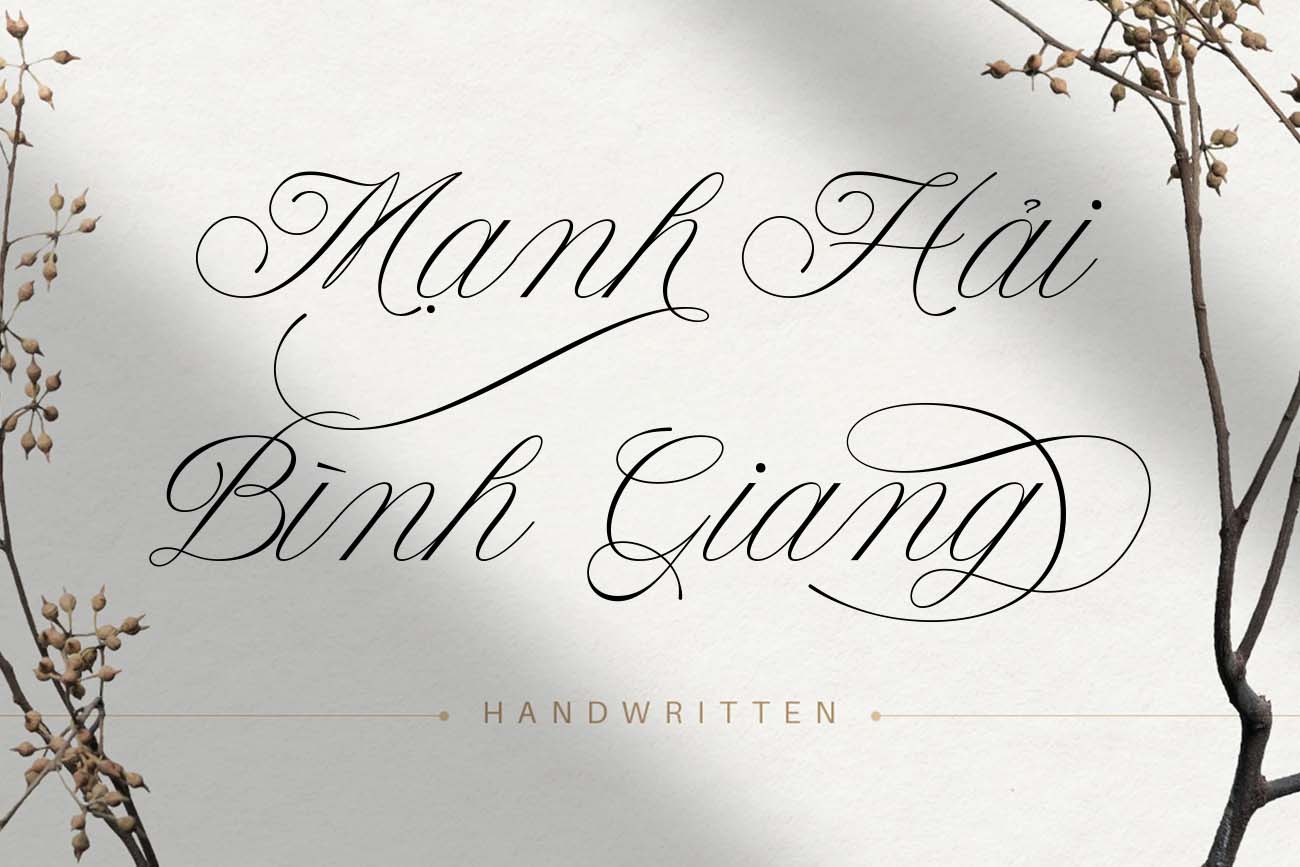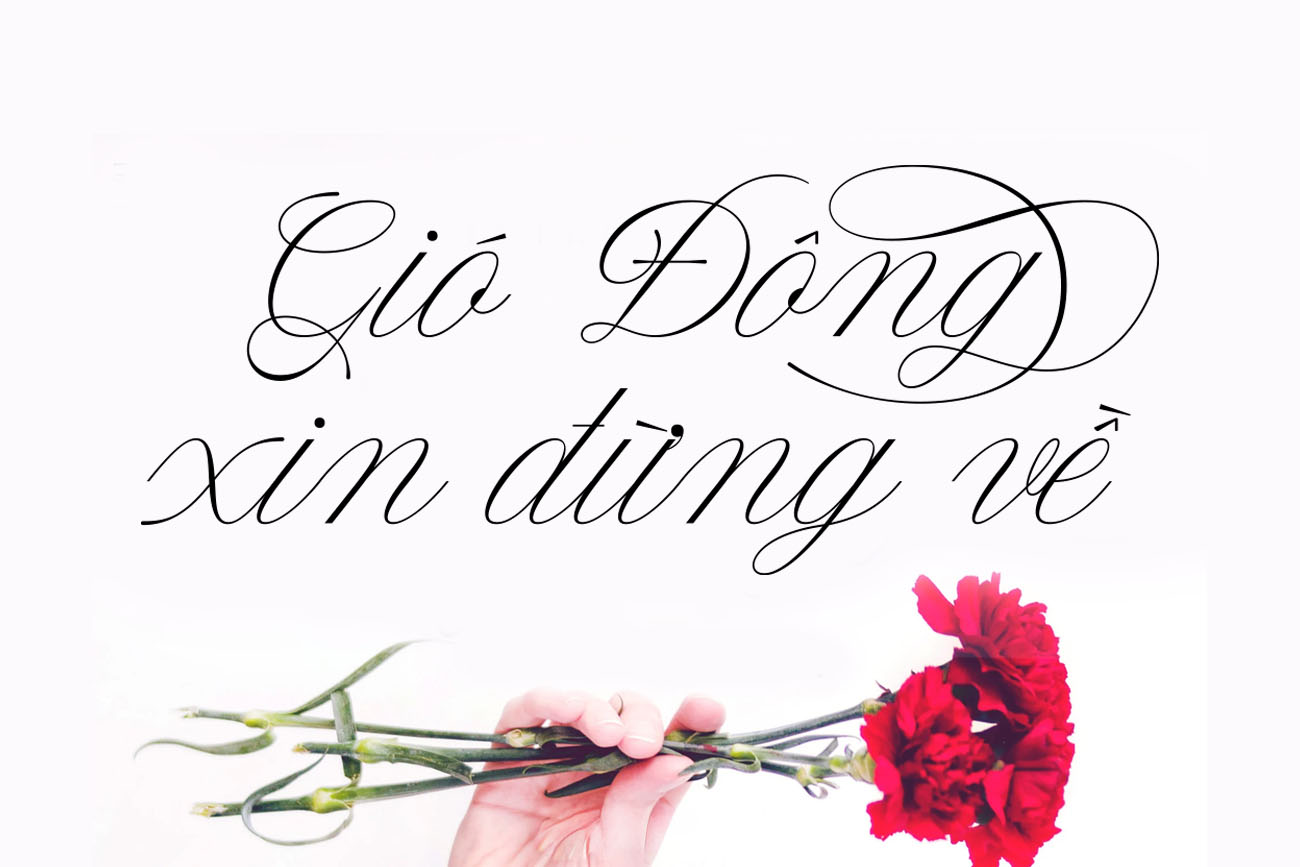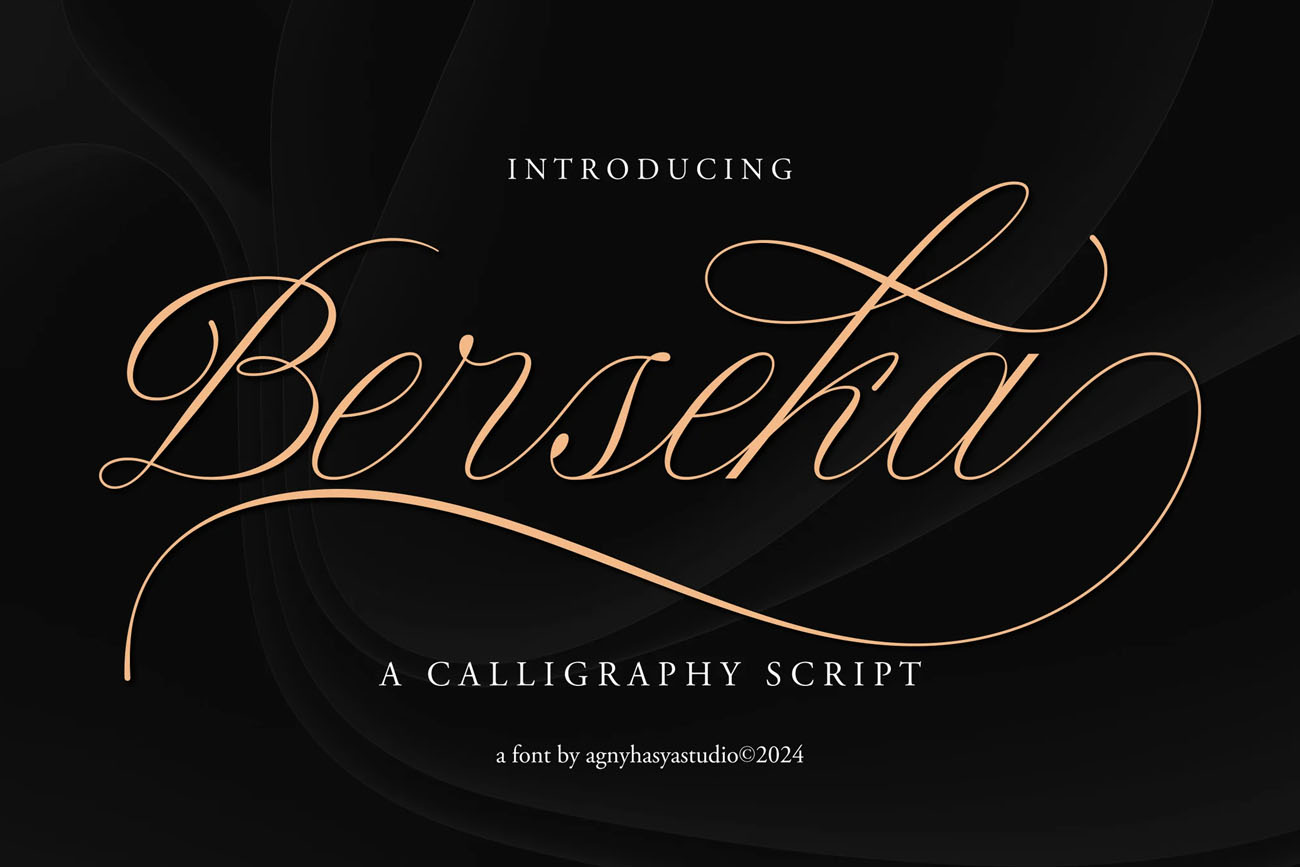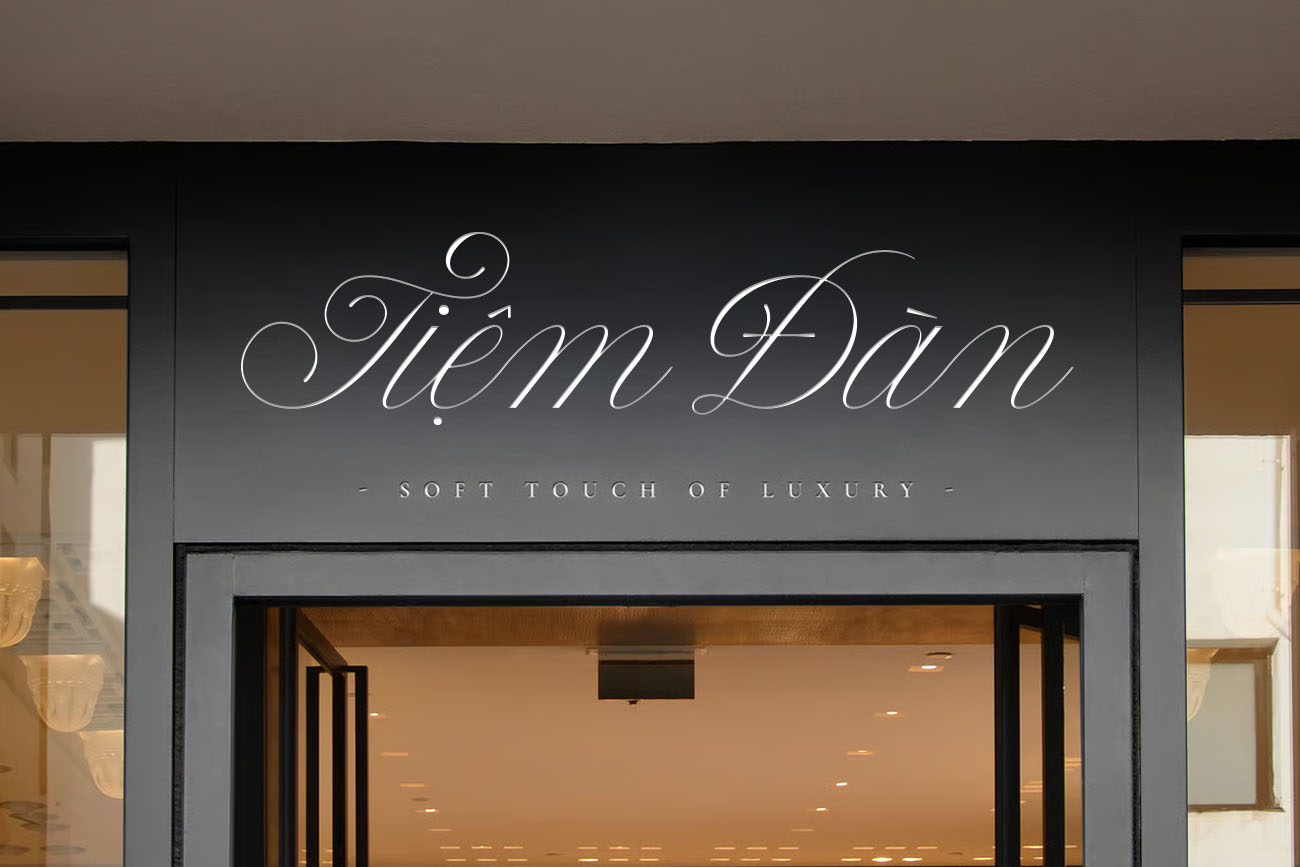
Font Calligraphy cho mùa cưới TH Berseka Việt hóa
Trong thế giới Typography đa dạng hiện nay, việc tìm kiếm một font chữ viết tay vừa giữ được nét phóng khoáng tự nhiên, vừa đảm bảo tính sang trọng và dễ đọc không phải là điều dễ dàng. Hôm nay, chúng tôi xin giới thiệu đến cộng đồng Designer bộ phông chữ TH Berseka – một tác phẩm nghệ thuật chữ viết đầy cảm xúc, hứa hẹn sẽ là trợ thủ đắc lực cho các dự án thiết kế cao cấp của bạn.
Vẻ đẹp hiện đại từ Agnyhasya Studio
TH Berseka có nguồn gốc từ bộ font Berseka nổi tiếng, được sáng tạo bởi Agnyhasya Studio. Đây là một dạng phông chữ Calligraphy Script hiện đại với các đường cơ sở (baseline) nhún nhảy đầy ngẫu hứng. Điểm thu hút nhất của bộ font này chính là sự thay đổi linh hoạt giữa các nét thanh và nét đậm, tạo nên một font uốn lượn vô cùng tinh tế, mềm mại nhưng không hề gây cảm giác rối mắt hay rườm rà.
Mỗi ký tự trong Berseka đều được trau chuốt tỉ mỉ để mô phỏng lại nét mực viết tay chân thực nhất, mang đến cái hồn nghệ thuật cho bất kỳ tác phẩm nào sử dụng nó.
Lựa chọn hàng đầu cho thiết kế thiệp cưới
Với vẻ đẹp lãng mạn và bay bổng đặc trưng, TH Berseka dường như được sinh ra để dành cho những sự kiện trọng đại của lứa đôi. Đây được xem là font thiệp cưới lý tưởng giúp các Designer truyền tải trọn vẹn thông điệp hạnh phúc và sự trang trọng.
Sự kết hợp giữa nét cổ điển và hơi thở hiện đại khiến TH Berseka trở thành font chữ đám cưới được săn đón nhiều nhất hiện nay. Không chỉ dừng lại ở thiệp mời, bạn hoàn toàn có thể ứng dụng font chữ này cho các hạng mục trang trí tiệc cưới (wedding stationery), bảng tên cô dâu chú rể, hoặc các video phóng sự cưới đầy chất thơ. Ngoài ra, tính thẩm mỹ cao của TH Berseka còn cực kỳ phù hợp cho thiết kế Logo, Branding thời trang, bao bì mỹ phẩm và các tiêu đề tạp chí.
Phiên bản Việt hóa hoàn chỉnh từ team TH
Mặc dù bản gốc Berseka đã rất xuất sắc, nhưng rào cản ngôn ngữ thường khiến các Designer Việt gặp khó khăn khi bỏ dấu. Hiểu được điều đó, đơn vị TH đã thực hiện Việt hóa trọn vẹn bộ font này với tên gọi TH Berseka.
Phiên bản TH Berseka không chỉ đơn thuần là thêm dấu tiếng Việt, mà còn được đội ngũ thực hiện tinh chỉnh lại khoảng cách (kerning) và tối ưu hóa các ký tự để đảm bảo sự mượt mà nhất khi gõ. Nhờ tâm huyết của team TH, giờ đây bạn có thể thỏa sức sáng tạo các nội dung tiếng Việt trên nền tảng font chữ đẳng cấp này mà không lo lỗi font hay mất thẩm mỹ.
Lời kết